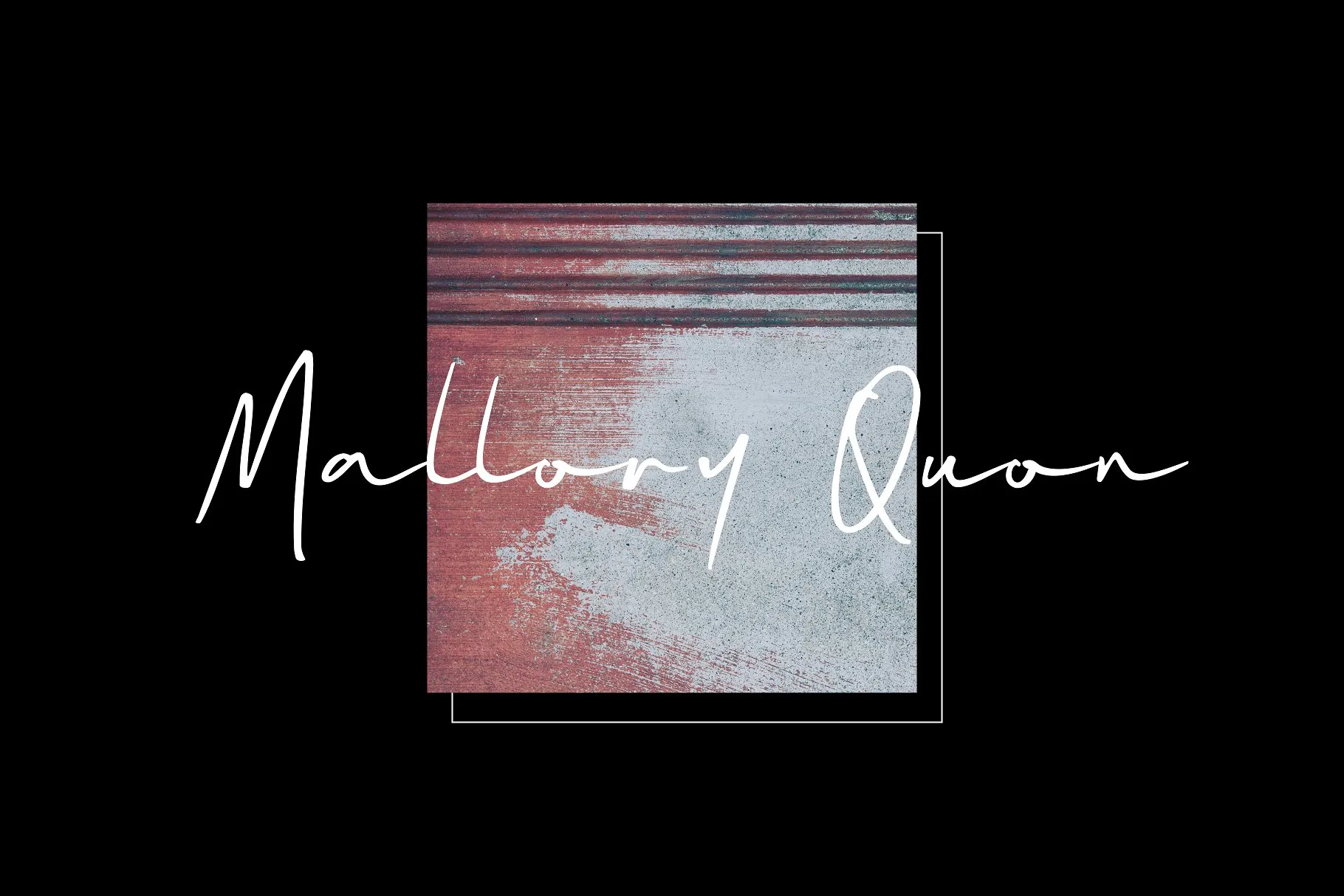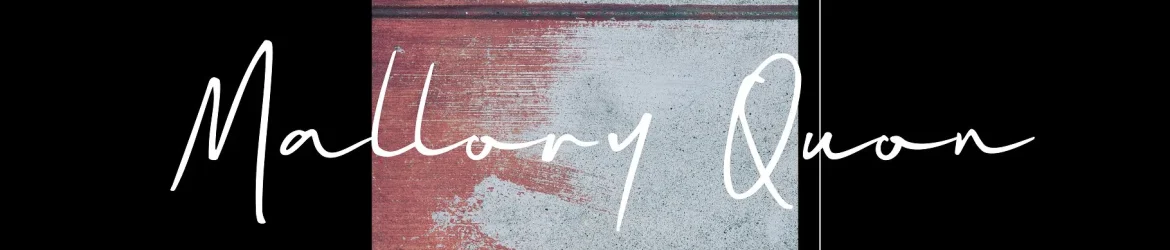
Mallory Quon Signature Font – Download Grátis
A Mallory Quon Signature Font é uma elegante escolha para designers que buscam adicionar um toque autêntico a seus projetos. Desenvolvida por zuzulgo, esta fonte script casual e moderna possui um estilo de escrita cuidadosamente elaborado. Ideal para um amplo espectro de aplicativos, desde logos e marcas até criações gráficas como invitations, wedding designs, etiquetas de produto ou mesmo postagens em redes sociais. A Mallory Quon é uma fonte perfeita para inovar com originalidade nos seus projetos. Seja para embalagens de produtos, campanhas publicitárias, fotografias, logotipos e marca pessoal, esta fonte trará um touch único à sua criação. Composta por linhas sutis e acabamentos meticulosamente detalhados, a Mallory Quon é perfeita para qualquer projeto onde deseja expressar elegância e personalidade.